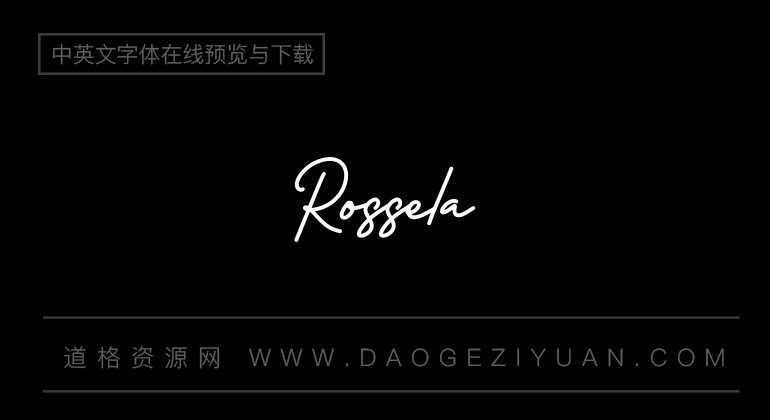
Rossela
Rossela 是一款由西班牙设计师José Scaglione为TipoType所设计的一款新型字体。它是一款综合性字体,既可以用于标题,也可以用于正文,具有流畅的线条和清晰的字形,使其看起来更加精致大方。它具有良好的读写性能,可以适应各种不同的语言,并且可以完美的表达文字的含义。此外,它还具有良好的可读性,可以使文字更加清晰,更加易读。
Rossela是一款非常不错的手写艺术字体,具有很好的视觉感,适合于文化类的宣传设计、商业类品牌的广告和产品包装设计以及个性化文字排版等较多场景。